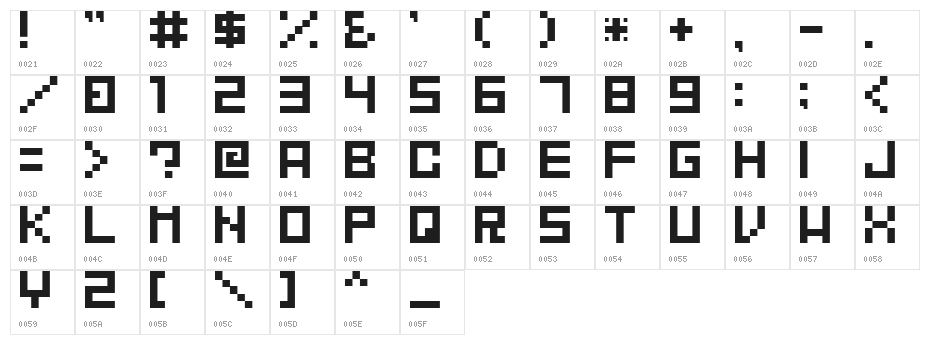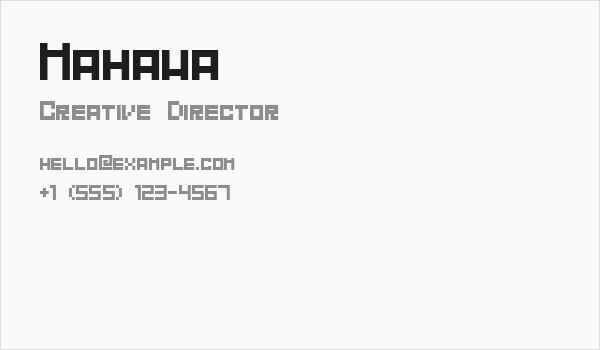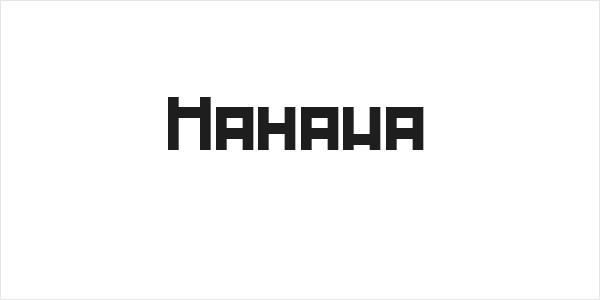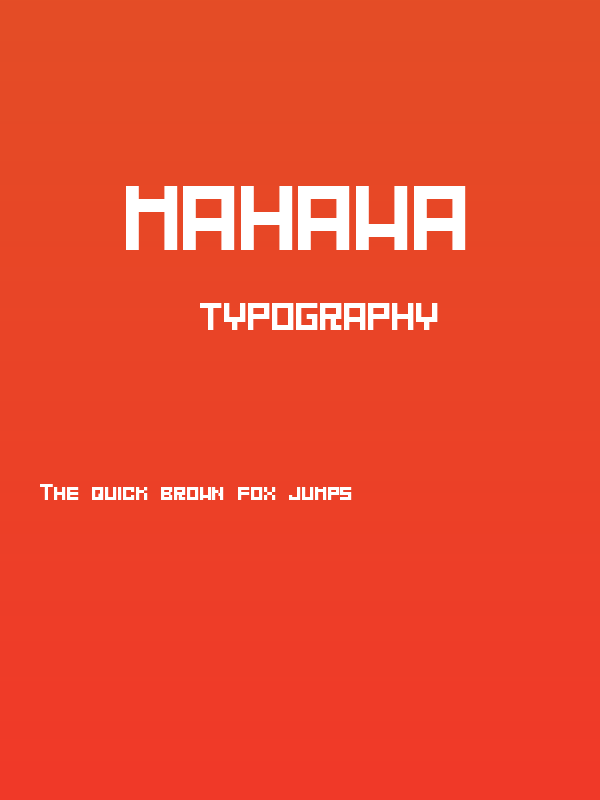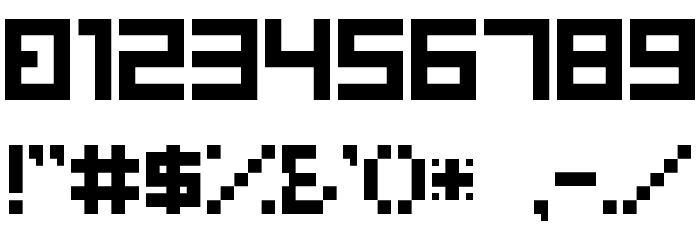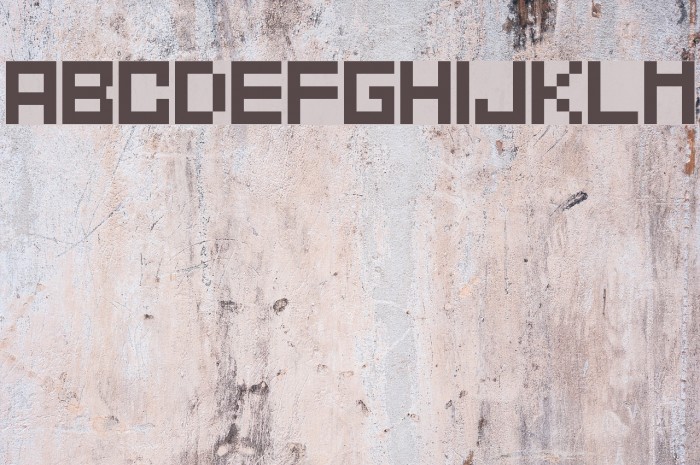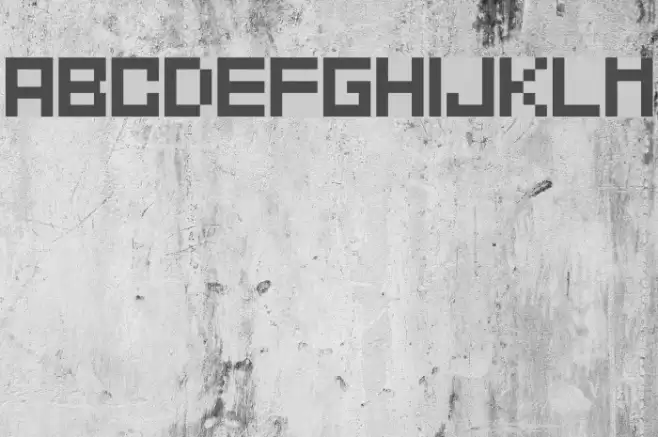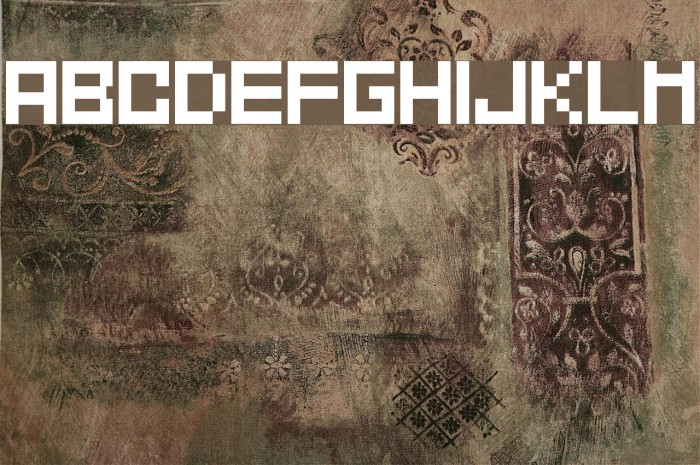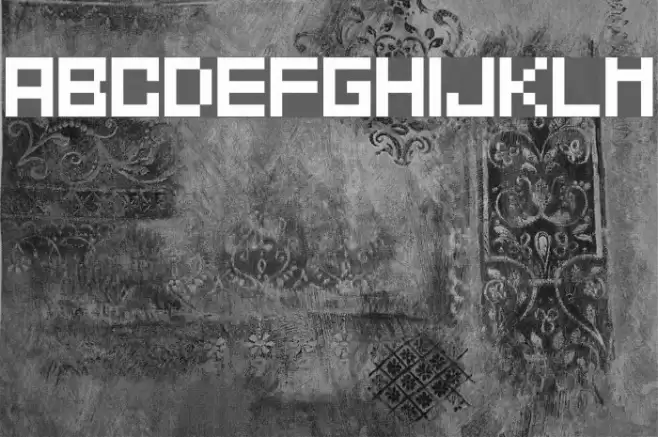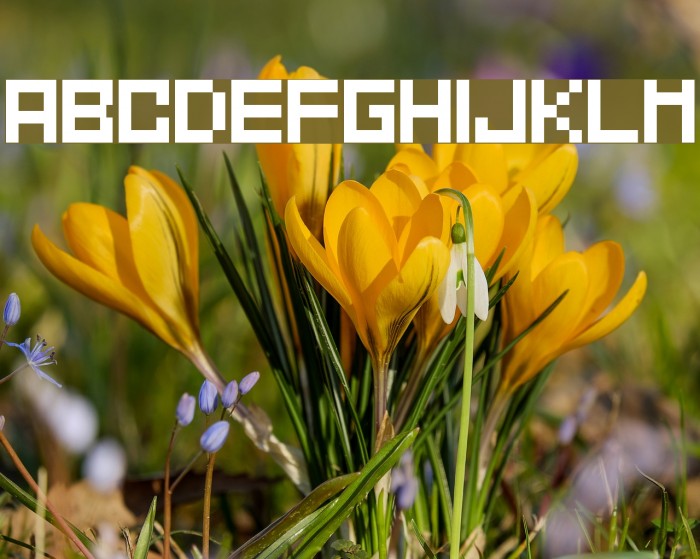
Mahawa Font
| समग्र शैली | Retro, Digital |
| उपयोग का मामला | Headlines, Logos, Posters |
| सुझाए गए प्रोजेक्ट | Ideal for video game design, tech-themed posters, retro digital art, and any project requiring a nostalgic or digital look. |